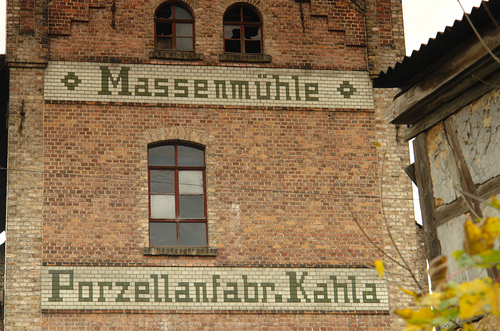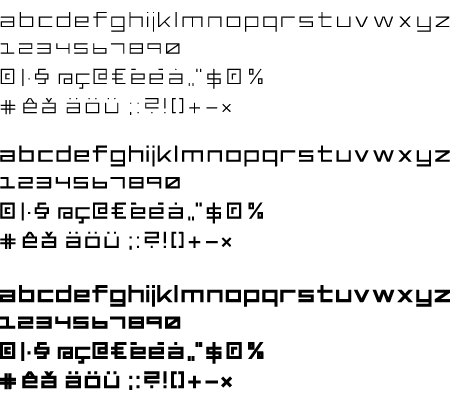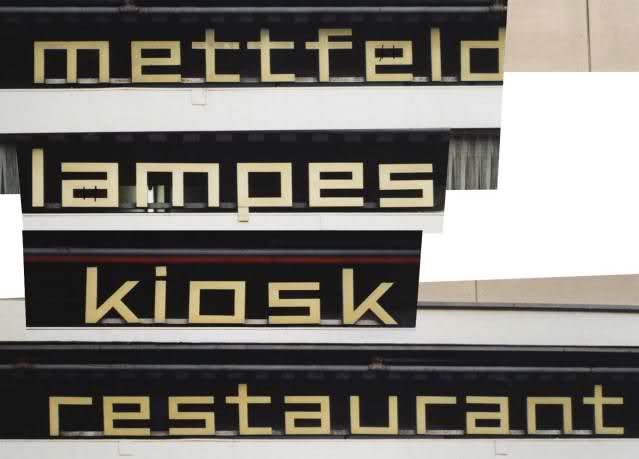
geometrische schriften -- oft schon gesehen -- keine infos?!
ich bin auf der suche nach einer schrift oder besser gesagt schriftsippe, die ich immer wieder in verschiedenen modifikationen auf schildern und als leuchtreklame in der schweiz angetroffen habe. im grunde sind es sehr klare und streng geometrisch konstruierte buchstaben, die heutzutage gerne an pixelschriften erinnern, aber sicherlich damals nix damit zu tun hatten. es gibt nach meiner recherche auch zahllose ähnliche schriften, die aber meist in einigen glyphen nur sehr flapsig hingezimmert sind.
zum ersten mal bin ich in der schweiz auf solch eine schrift gestossen als leuchtreklame. an einer schule in unserem ort sind die buchstaben in den beton gegossen worden. die simple konstruktion eignet sich halt auch sehr gut für grobstolligere anwendungen. desweiteren gibt es auch einige baufirmen, wie z.b. max bögl - http://www.max-boegl.de/boeglnet/web/show.jsp - oder georg moll - http://www.moll-tiefstrassenbau.de/ oder den farbenhersteller sikkens - http://www.sikkens.de - die mit ähnlich konstruierten schriftzügen oder signets ausgestattet wurden.
meine vermutung ist ja, dass das alles reklameschriften aus den 60ern waren bzw. sind, die nicht digitalisiert sind. ich habe es mir nebenbei halt zum hobby gemacht einerseits fontlab zu lernen an solch einer schrift, aber auch die konstruktion dieser vordergründig sehr einfach gestrickten schriftsippe zu analysieren und auszuloten, inwieweit man mit einer archaischen und simplen geometrie doch eine ästhetisch ansehnliche schrift gestalten kann.
hier ein kleines bildchen der ersten gehversuche und als anschauungsmaterial:
Deine Vermutung ist IMHO zutreffend. Diese Schriften wurden einfach aus Rechtecken konstruiert. Die von Dir gezeigten Schriften unterscheiden sich deshalb auch. Es gibt aber auch schon einige elektronische Schriften dieser Art.
SF Square Head:
Imagine Font:
Angie's New House:
Tutor:
Flight Corps:
solche schriften gehen meist auf 'de stijl' zurück, eine art 'niederländischer bauhausstil'.
schaffenszeit war 1917 — 1931, Theo van Doesburg und Piet Mondrian sind wohl die bekanntesten künstler dieser zeit.
Schau Dir auch mal Tschicholds „leicht und schnell konstruierbare Schrift“ an:
Das ist komisch! An diese habe ich auch gedacht, aber nicht darauf hingewiesen weil diese IMHO schon zu unklotzig ist. Beachte die Rundungsradien die so in den gezeigten Beispielen nicht auftauchen. Aber interessant ist diese Schrift auf jeden Fall.
solche schriften gehen meist auf 'de stijl' zurück, eine art 'niederländischer bauhausstil'.
Bei den Leuchtreklametafeln gehen diese Schriften in erster Linie auf ,,Bequemlichkeit'' und Sparsamkeit zurück. In der pre-CNC-Ära war dies die einfachste und preiswerteste Art eine Schrift zusammenzubauen. Da war IMHO ,,de stijl'' nur das Alibi. Man sollte nie die harten Randbedingungen von Technik und Wirtschaftlichkeit vergessen. ;-)
hey super, vielen dank für eure antworten. in den 20er jahren hab ich mich auch schon etwas rumgetrieben, die "schriften" bewegten sich schon recht stark in richtung grafisches bild und waren sehr streng von rastern geprägt. auf die eigenheiten der einzelnen buchstaben und deren erkennbarkeit/lesbarkeit wurde kaum augenmerk gelegt.
jüngst hatte ich auch in anzeigen der sony-playstation eine ähnliche auffassung gesehen. mal sehen, ob ich in einiger zeit hier mal posten kann, dass die schriftfamilie fertig ist. ich sitze da auch noch an rounded-versionen, die ja dem entwurf recht nahe liegen.
hier mal noch als nachreichung die orginal-leuchtreklamen aus der schweiz:
bequemlichkeit und sparsamkeit? dem würde ich wiedersprechen.
es gibt genügend beispiele wo man sieht das es früher auch anders ging. er fragte ja vorallem nach den geschichtlichen hindergründen. reduzierung und abstraktion wie sie auch beim bauhaus oder konstruktivismus zu finden sind haben diese formen geprägt und wurden dann später immer wieder gern übernommen. neville brody, wim crouwel und viele andere designer haben diesen stil dann später fortgeführt.
gerade bei baufirmen bieten sich diese 'klotzigen' formen ja an, denn der konstruktivismus ist ja auch ein typischer baustil in der architektur.
Ist jemanden ein (möglichst modernes) Buch bekannt, das sich solchen Zuordnungen etwas ausführlicher widmet, als es z. B. in „Wegweiser Schrift“ der Fall ist, wo nicht eine Schrift in der Matrix gezeigt wird, die der hier gezeigten entspricht.